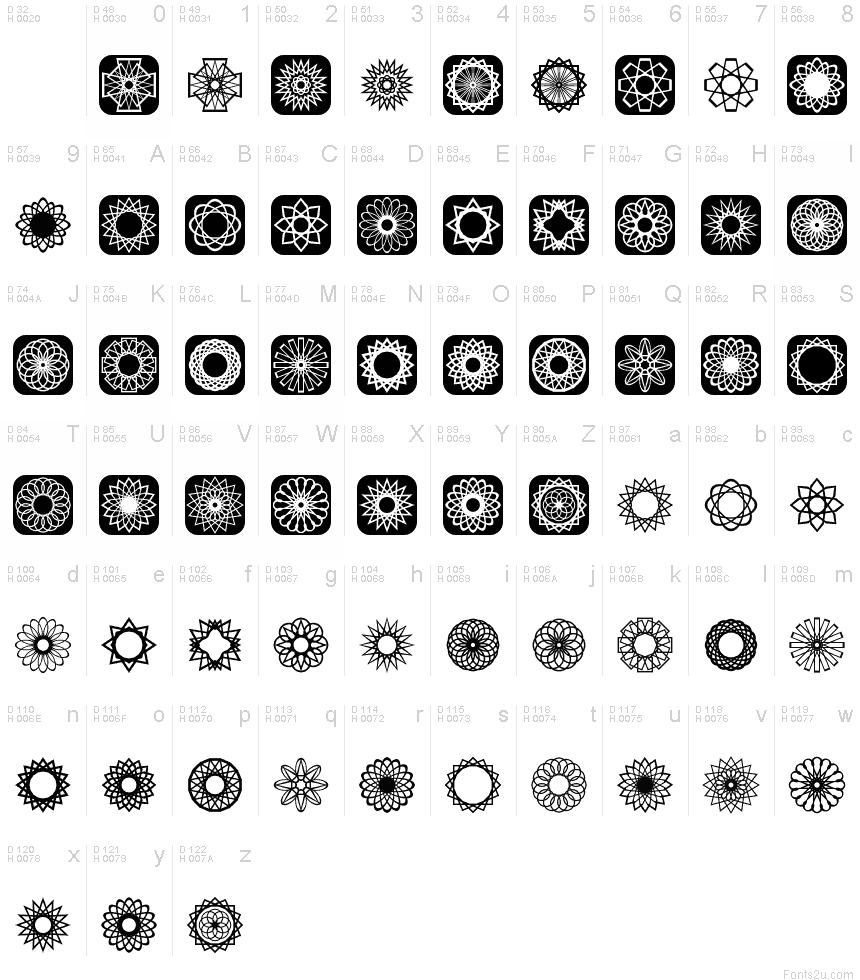
Symmetric Things 2 von Fonts n Things ist eine kostenlose geometrische Dingbat-Schrift, die auf strahlenförmigen Rosetten, Sternen und medaillonartigen Symbolen basiert. Das Set wirkt esoterisch und ornamentreich; dank sich wiederholender Blütenblätter, Speichen und mehrschichtiger Konturen erinnern die Formen eher an Abzeichen, Siegel oder mandalaartige Embleme als an einfache Icons.
Es passt perfekt für Verpackungen, Poster-Akzente, Einladungen, Scrapbooking-Grafiken und Logoeinrahmungen – überall dort, wo eine kostenlose Schrift mit dieser kreisförmigen Symmetrie schnell ein dekoratives Element oder Emblem liefert. Nutzen Sie sie für Kapitelmarkierungen, Titelkarten, Label-Mitten oder kleine Branding-Momente, wenn ein in sich geschlossenes, ausgewogenes und feierliches Motiv gefragt ist.
Symmetric Things 2